Capitalis Monumentalis
Die »Capitalis Monumentalis« ist eine lateinische, in Stein gemeißelte Schrift; Lapidarschrift; Schrift der Römer. Die Capitalis Monumentalis ist eine Adaption des eteokretisch-griechischen Alphabets, welches um 600 v.Chr. aus dem multikulturellen Kreta über die Etrusker – »dem Volk der Bücher« – zu den Latinern ins heutige Mittel- und Nordwestitalien gelangte, deren römische Nachkommen daraus die lateinische Schrift entwickelten.
Die Paläografie und Epigraphik nennt diese lateinische Schrift »Capitalis monumentalis«. 1) Etymologisch aus lat. »capitalis« für »Haupt, Kopf«, aus »den Kopf, das Leben betreffend; in seiner Art vorzüglich«, und »monumentalis« für »monumental, sehr groß«.
Die Capitalis Monumentalis ist eine römische Majuskelschrift, also eine Schrift, die nur aus Majuskeln besteht. Ihre Typometrie orientiert sich deutlich an Quadrat, Kreis und Dreieck.
Die Inschriften in Naturwerkstein wurden vor der Einmeißelung von Steinbildhauern bzw. Steinmetzen vermutlich mit einem Flachpinsel im Zweiliniensystem vorgeschrieben, um die Fernwirkung, das Spiel von Licht und Schatten oder spätere Auffüllungen mit Farbpigmenten (siehe Serifen) zu beurteilen bzw. für einen Auftraggeber zu simulieren.
Daraufhin wurden die Konturen der Schriftzeichen im Sinne einer stereotypen Letternarchitektur für die Meißelführung – möglicherweise mit einem eingefärbten Griffel – konkretisiert bzw. eingeritzt und schlussendlich eingemeißelt. Typisch für die römische Capitalis Monumentalis, die als das Vorbild aller Antiquaschriften gilt, sind die Serifen.
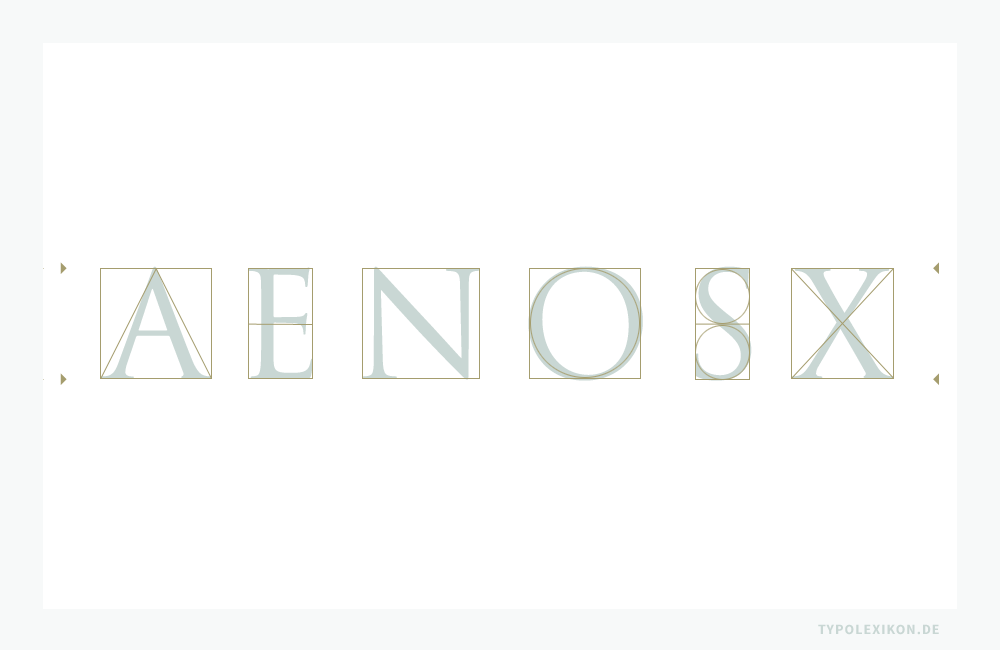
Das älteste Zeugnis für die Schrift der Römer ist eine Epigraphik auf einer zylindrischen Tuffstein-Stele, dem Cippus der Sakralstätte »Lapis Niger« auf dem Forum Romanum im Bereich des Comitium in Rom, die vermutlich aus dem 6. vorchristlichen Jahrhundert stammt; ihre lateinischsprachige Inschrift ergibt, mit Ausnahme des Buchstabens B, ein vollständiges Alphabet, das formal noch genau dem westgriechischen Typus der schon von Herodot von Halikarnass (um 490/480–um 430/420 v.Chr.) als »grammata phoinikeia« bezeichneten altsemitischen Urbuchstaben entspricht. In der Folge entstand daraus das klassische römische Alphabet mit seinen 21 modifizierten, nunmehr lateinischen Buchstaben, das im ersten vorchristlichen Jahrhundert durch die griechischen Originalzeichen Ypsilon und Zeta auf 23 Buchstaben vervollständigt wurde. 2)
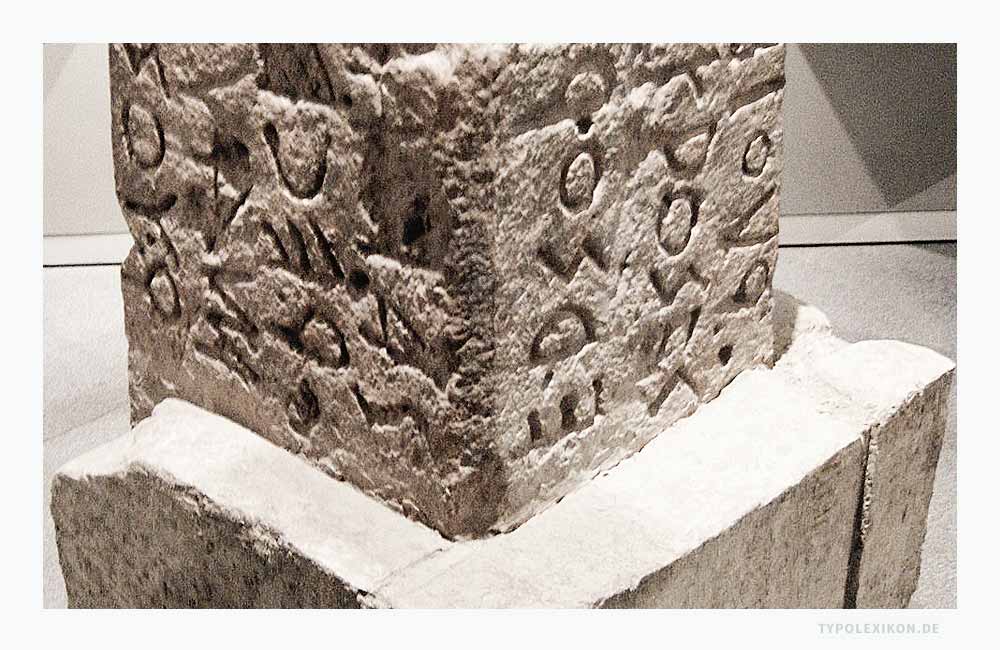
In der Paläografie wird die römische Schrift generell als »Scriptura capitalis« bezeichnet. Zu dieser Zeit ist auch bereits die Darstellung von Zahlen mit sieben Majuskeln aus dem Alphabet der Scriptura Capitalis ausgereift; ein additives Zahlenzeichensystem, welches wir heute auch als »Römische Zahlen« bezeichnen.
Das berühmteste Beispiel für die Capitalis Monumentalis ist die Inschrift auf dem Sockel der »Columna Traiana«, der »Trajanssäule«, die im Frühjahr 113 von Apollodoros nach den persönlichen Anweisungen des römischen Kaisers auf dem Trajansforum in Rom fertiggestellt wurde. Dieses »Trajanische Alphabet« gilt als das schönste Beispiel römischer Schriftkunst. 3) 4) 5) 6)
Aus der in Stein gemeißelten Capitalis Monumentalis entwickelten sich zwei handschriftliche Schriftvarianten: die »Capitalis quadrata« (Römische Quadratschrift) für Pergamenthandschriften und die »Capitalis rustica« als eine Schnellschreibvariante davon. Die Capitalis Quadrata und die Capitalis Rustica gelten als die klassischen Buchschriften der Römer. Als Verkehrsschrift benutzten sie eine »Cursiva«, die mit einem Griffel in Wachstafeln oder mit einer sehr schmalen Rohrfeder auf Papyrus geschrieben wurde.
Die Eroberungsfeldzüge der Römer sorgten schließlich für die weitere Verbreitung und Durchsetzung dieser Schreibtechnologie, die mit ihren Stilvarianten zur produktivsten der gesamten Schriftgeschichte werden sollte.
| ↑1 | Anmerkung: Der gebräuchliche Terminus »Capitalis monumentalis« ist eine neuzeitliche Terminologie. Er wurde vermutlich im späten 19. Jahrhundert eingeführt und setzte sich im frühen 20. Jahrhundert als Standardbezeichnung für die römische Monumentalschrift durch. So verwendet beispielsweise bereits der Charlottenburger (heute ein Ortsteil von Berlin) Philologe und Epigraphiker Emil Hübner (1834–1901) in seinem Standardwerk »Exempla scripturae epigraphicae Latinae a Caesaris dictatoris morte ad aetatem Iustiniani. Consilio et auctoritate Academiae Litterarum Regiae Borussicae edidit Aemilius Hübner«. Berolini: Apud G. Reimerum, 1885 (Auctarium Corporis Inscriptionum Latinarum), die Unterscheidung zwischen monumentalen und handschriftlichen Capitalis-Formen. Allerdings ist nach den derzeit zugänglichen Quellen nicht verifizierbar, ob Hübner bereits die feste Wortverbindung »Capitalis monumentalis« verwendete oder sogar prägte. |